싸인을 만들 때, 명품 브랜드 로고에서 영감을 얻을 수 있어요. 명품 로고는 단순하면서도 세련된 디자인을 가지고 있어, 고급스러운 느낌을 줄 수 있기 때문이에요. 💎
예를 들어, 샤넬(CHANEL)의 로고는 간결하면서도 품격을 강조하며, 루이비통(Louis Vuitton)의 모노그램은 브랜드의 아이덴티티를 강하게 각인시켜요. 이러한 요소를 싸인에 반영하면, 한층 더 세련되고 인상적인 싸인을 만들 수 있어요! ✍️
그렇다면, 싸인과 브랜드 로고의 관계는 어떤 특징이 있을까요? 🔥
싸인과 브랜드 로고의 관계 🔗
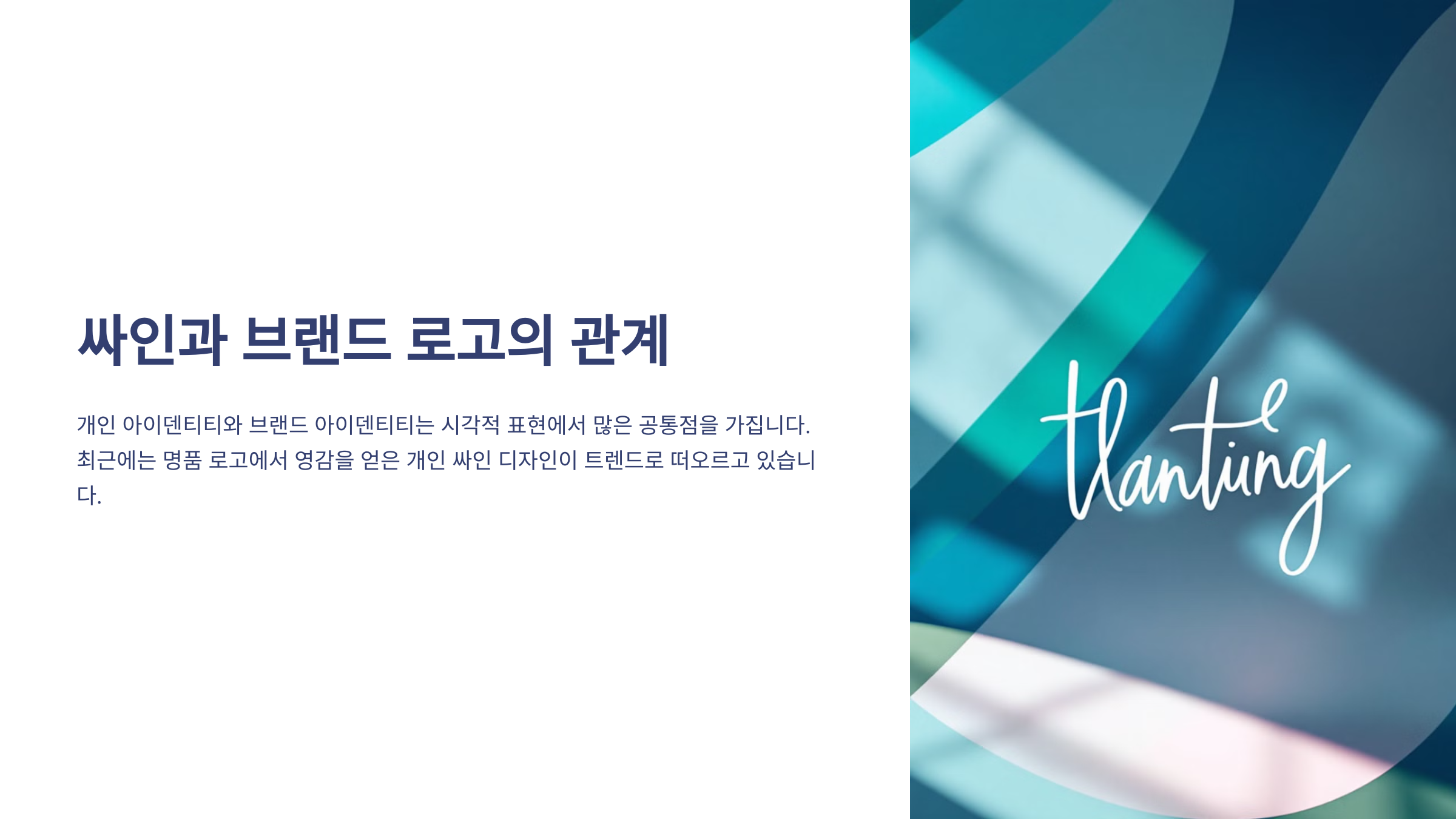
싸인과 브랜드 로고는 단순한 서명이 아니라, 자신의 개성과 가치를 표현하는 중요한 도구예요. 💎
명품 브랜드 로고는 시간이 지나도 변하지 않는 아이덴티티를 가지고 있으며, 싸인도 마찬가지로 한 번 정하면 오랫동안 유지되는 개인의 상징이 될 수 있어요. ✍️
📌 싸인과 명품 브랜드 로고의 공통점 ✅
공통점 설명 예시 고유한 정체성 개인을 상징하는 유니크한 요소 포함 샤넬 "CC" 로고, 나이키 "Swoosh" 간결하면서도 강렬한 디자인 복잡하지 않지만, 강한 인상을 줌 애플 로고, 루이비통 "LV" 시간이 지나도 변하지 않는 가치 한 번 정하면 오래도록 유지 롤렉스 크라운 로고 시그니처 효과 이름 없이도 브랜드나 사람을 인식할 수 있음 펜디 "FF", 마이클 잭슨의 싸인 이처럼 싸인과 브랜드 로고는 비슷한 특징을 공유하고 있어요. 그럼 이제 명품 브랜드 로고의 구체적인 디자인 특징을 살펴볼까요? 👑
명품 브랜드 로고의 특징 👑
명품 브랜드 로고는 단순하지만 강렬한 디자인을 가지고 있어요. 대부분 고유한 아이콘, 이니셜 조합, 세련된 서체를 활용하여 브랜드 가치를 강조하죠. 💎
예를 들어, 샤넬(CHANEL)의 "CC" 로고는 단순하지만 우아한 느낌을 주며, 루이비통(Louis Vuitton)의 "LV" 모노그램은 브랜드의 정체성을 강하게 각인시켜요. ✨
📌 명품 브랜드 로고의 주요 디자인 요소 🎨
디자인 요소 설명 예시 브랜드 이니셜 조합 브랜드의 첫 글자를 활용하여 심볼화 루이비통 "LV", 샤넬 "CC" 대칭적 디자인 균형감 있는 형태로 시각적 안정감 제공 구찌 "GG", 롤렉스 크라운 세련된 필기체 손글씨 스타일의 우아한 서체 활용 조르지오 아르마니, 디올 미니멀한 디자인 불필요한 요소 없이 단순하고 고급스러움 애플, 발렌시아가 명품 브랜드 로고는 고유한 스타일을 유지하면서도 단순하고 세련된 디자인을 갖추고 있어요. 그럼 이제 캘리그래피 스타일 로고를 활용한 싸인 디자인을 살펴볼까요? ✍️
캘리그래피 스타일 로고 ✍️
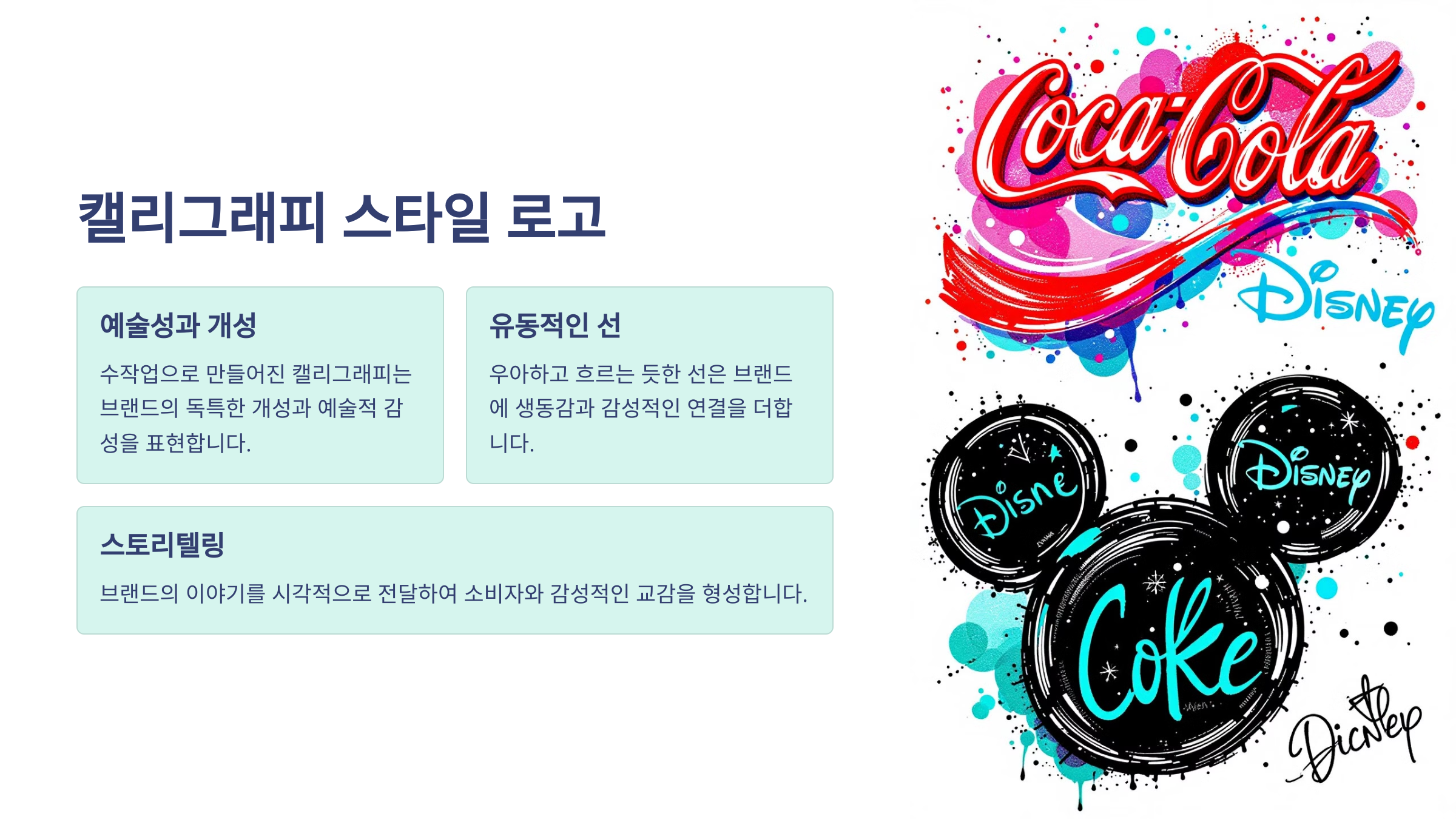
캘리그래피 스타일의 로고는 우아하고 세련된 필체를 활용하여 브랜드의 개성을 강조해요. 특히 패션 브랜드, 뷰티 브랜드, 고급 레스토랑에서 많이 사용되죠. 🎨
예를 들어, 디올(Dior)과 조르지오 아르마니(Giorgio Armani)의 로고는 고급스러운 필기체를 사용하여 브랜드의 품격을 나타내요. 💎
📌 캘리그래피 스타일 로고의 특징 🖋️
특징 설명 예시 브랜드 우아한 필기체 부드럽고 흐르는 듯한 글자 형태 디올(Dior) 곡선과 장식 강조 곡선적인 디자인을 활용하여 개성 표현 조르지오 아르마니(Giorgio Armani) 클래식한 감성 고전적인 아름다움을 강조 까르띠에(Cartier) 고급스러운 브랜드 이미지 브랜드의 가치와 품격을 표현 입생로랑(YSL) 캘리그래피 스타일은 우아한 분위기를 원하는 싸인 디자인에 적합해요! 그럼 이제 모노그램 스타일 로고를 활용한 싸인을 살펴볼까요? 🔤
모노그램 스타일 로고 🔤
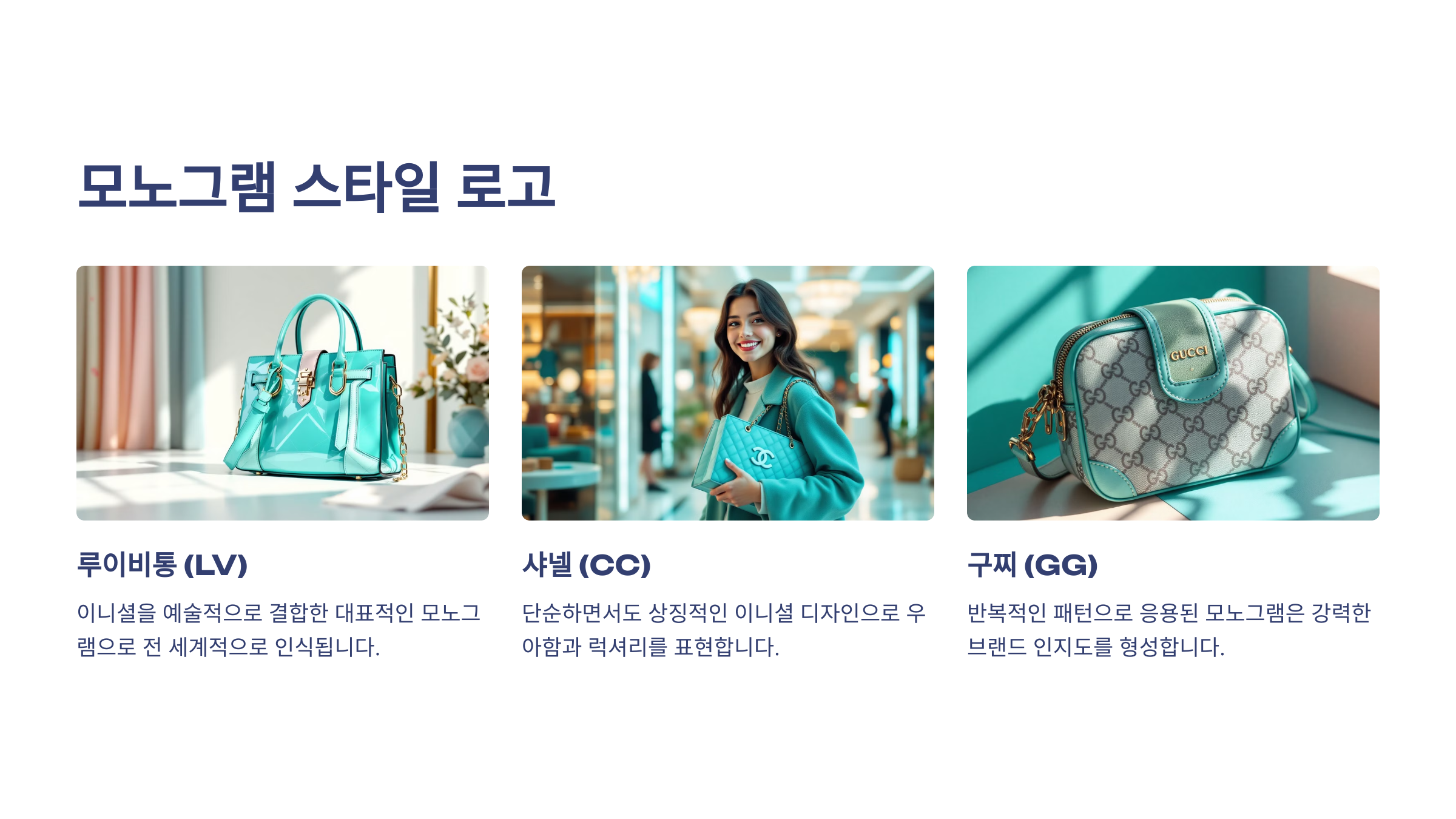
모노그램 스타일 로고는 브랜드의 이니셜을 조합하여 강렬한 아이덴티티를 형성하는 방식이에요. 특히 명품 패션 브랜드에서 많이 활용되며, 싸인 디자인에도 적용할 수 있어요. 💎
예를 들어, 루이비통(Louis Vuitton)의 "LV", 구찌(Gucci)의 "GG", 입생로랑(YSL) 로고는 단순하지만 고급스럽고 강렬한 브랜드 이미지를 전달해요. 🎨
📌 모노그램 스타일 로고의 특징 🏆
특징 설명 예시 브랜드 이니셜 조합 브랜드 이름의 앞글자를 디자인적으로 배치 루이비통 "LV" 대칭적이고 균형 잡힌 형태 글자 간격과 배치를 정교하게 맞춤 구찌 "GG" 타이포그래피 강조 독특한 글씨체를 활용하여 브랜드 개성 표현 입생로랑 "YSL" 시각적 인지도가 높음 한 번 보면 쉽게 기억할 수 있는 디자인 펜디 "FF" 모노그램 스타일은 단순하면서도 고급스러운 싸인을 만들고 싶을 때 참고하면 좋아요! 그럼 이제, 미니멀하고 세련된 스타일의 브랜드 로고를 활용하는 방법도 살펴볼까요? ✨
미니멀하고 세련된 로고 ✨
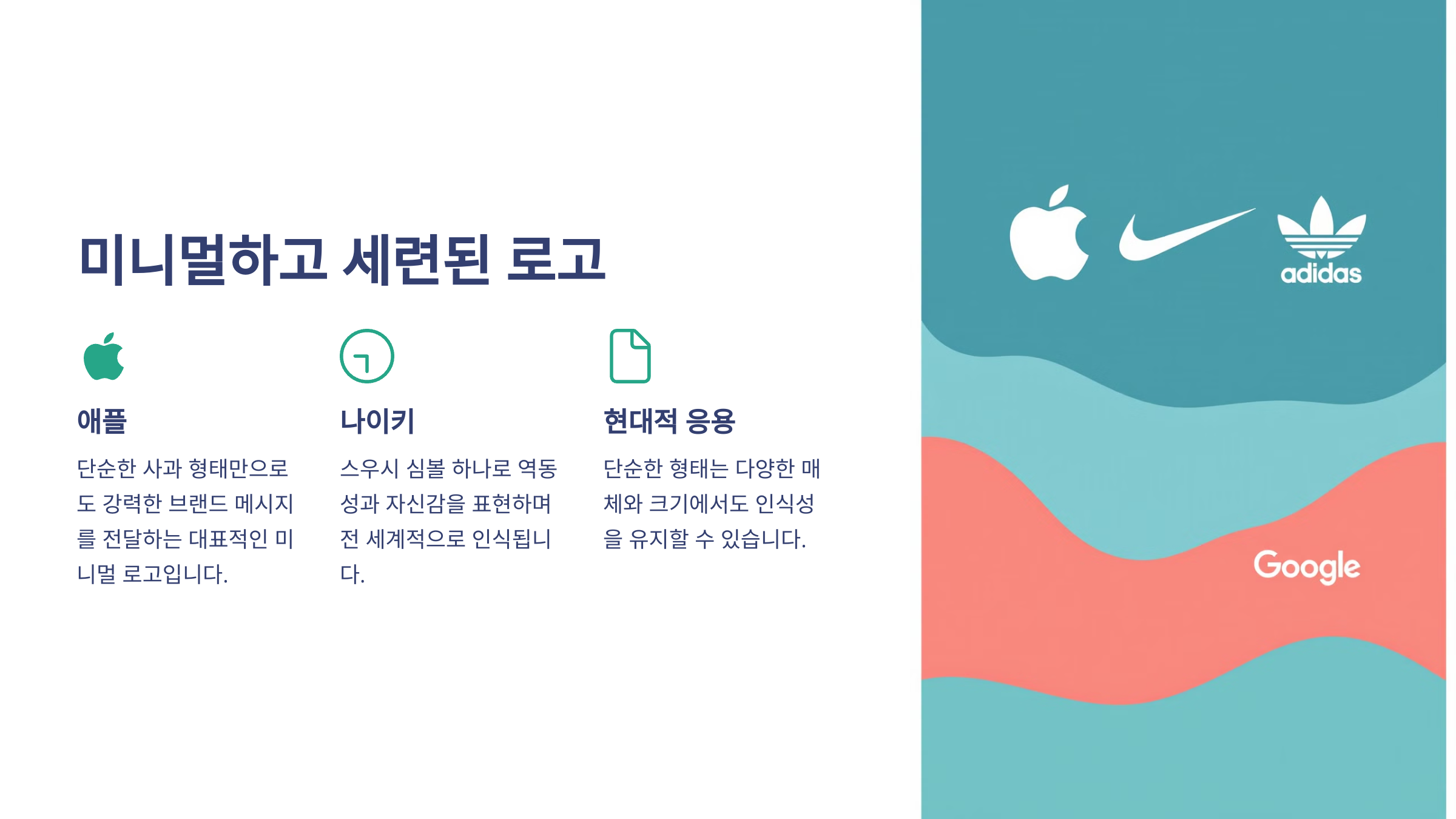
미니멀한 디자인은 불필요한 요소를 제거하고, 본질적인 아름다움을 강조하는 스타일이에요. 이는 싸인 디자인에서도 적용할 수 있으며, 깔끔하면서도 세련된 느낌을 줄 수 있어요. 💎
예를 들어, 애플(Apple), 발렌시아가(Balenciaga) 같은 브랜드는 최소한의 요소만 사용하여 강렬한 브랜드 이미지를 구축했어요. 🔥
📌 미니멀한 스타일 로고의 특징 🎨
특징 설명 예시 브랜드 단순한 타이포그래피 깔끔한 글씨체만 사용하여 브랜드 이미지 전달 발렌시아가(Balenciaga) 불필요한 요소 제거 장식 없이 직관적인 디자인 애플(Apple) 균형과 정렬 글자 간격과 형태의 정교한 조화 마르니(Marni) 색상 최소화 단색 또는 블랙&화이트 활용 셀린(Celine) 미니멀한 스타일은 심플하면서도 강렬한 인상을 남길 수 있어요. 이제 명품 로고의 특징을 활용해 나만의 싸인을 디자인하는 방법을 알아볼까요? ✍️
명품 로고를 참고해 싸인 디자인하는 법 ✍️
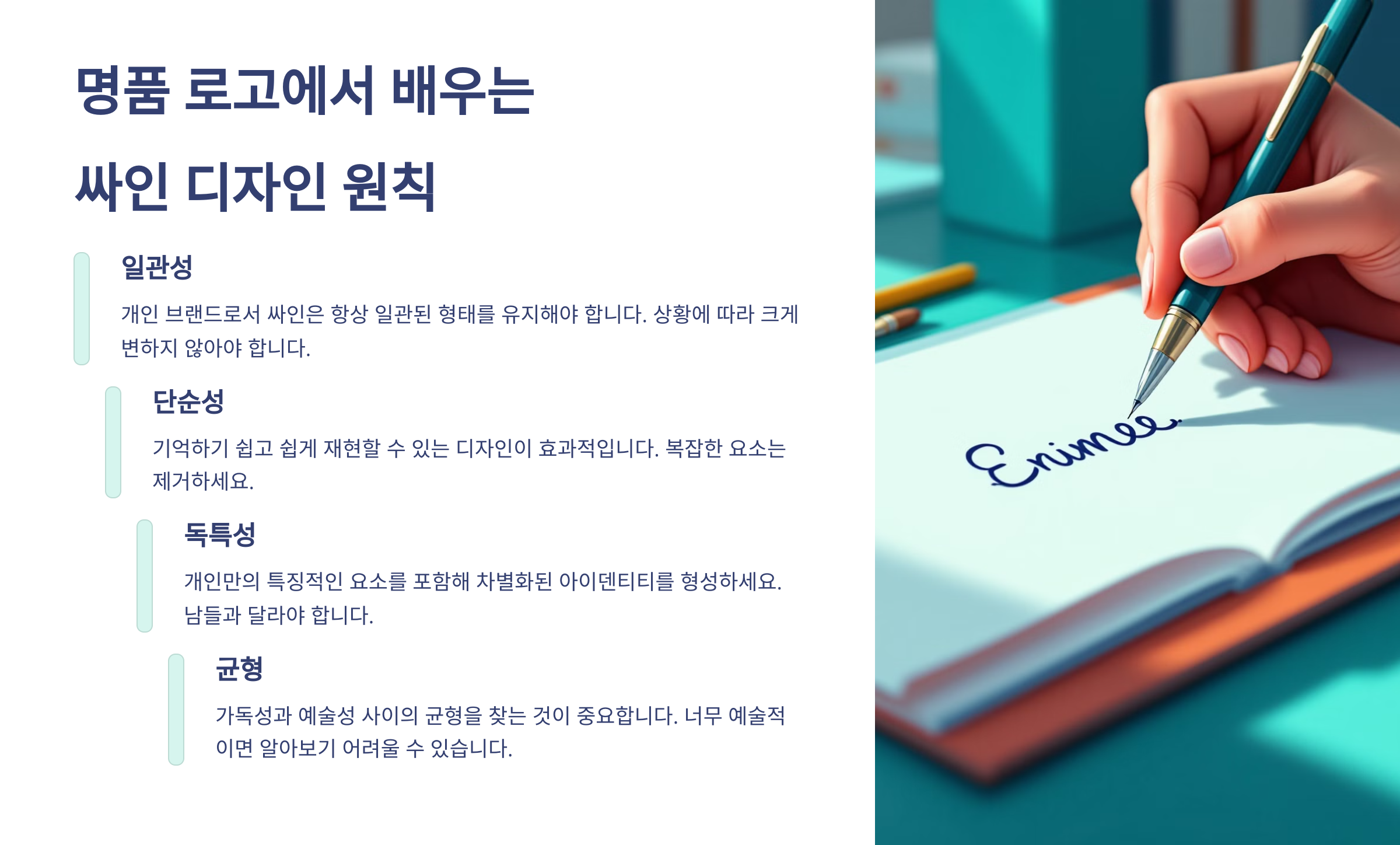
명품 브랜드 로고의 디자인 원칙을 활용하면, 단순하면서도 고급스럽고 개성 있는 싸인을 만들 수 있어요. 💎
지금부터 명품 브랜드 로고에서 배울 수 있는 싸인 디자인 원칙을 알려드릴게요. 🚀
📌 명품 로고를 활용한 싸인 디자인 5단계 ✅
단계 설명 참고 브랜드 1. 간결한 형태 유지 복잡한 장식을 피하고 핵심 요소만 남기기 샤넬(CHANEL), 애플(Apple) 2. 이니셜 활용 이름의 첫 글자를 활용해 스타일링 루이비통(LV), 구찌(GG) 3. 필기체 또는 정형화된 서체 선택 우아한 필기체 또는 세련된 타이포그래피 활용 디올(Dior), 입생로랑(YSL) 4. 균형과 대칭 유지 글자 간격과 정렬을 맞춰 안정적인 디자인 롤렉스(Rolex), 마르니(Marni) 5. 자신만의 포인트 추가 별(★), 밑줄, 곡선 등 개성을 살리는 요소 추가 마이클 잭슨의 싸인, 펜디(FF) 이제 명품 브랜드 로고의 특징을 반영한 나만의 싸인을 만들 준비가 되었어요! 마지막으로, 싸인과 브랜드 로고에 대한 자주 묻는 질문(FAQ)을 정리해 볼게요. 📢
FAQ
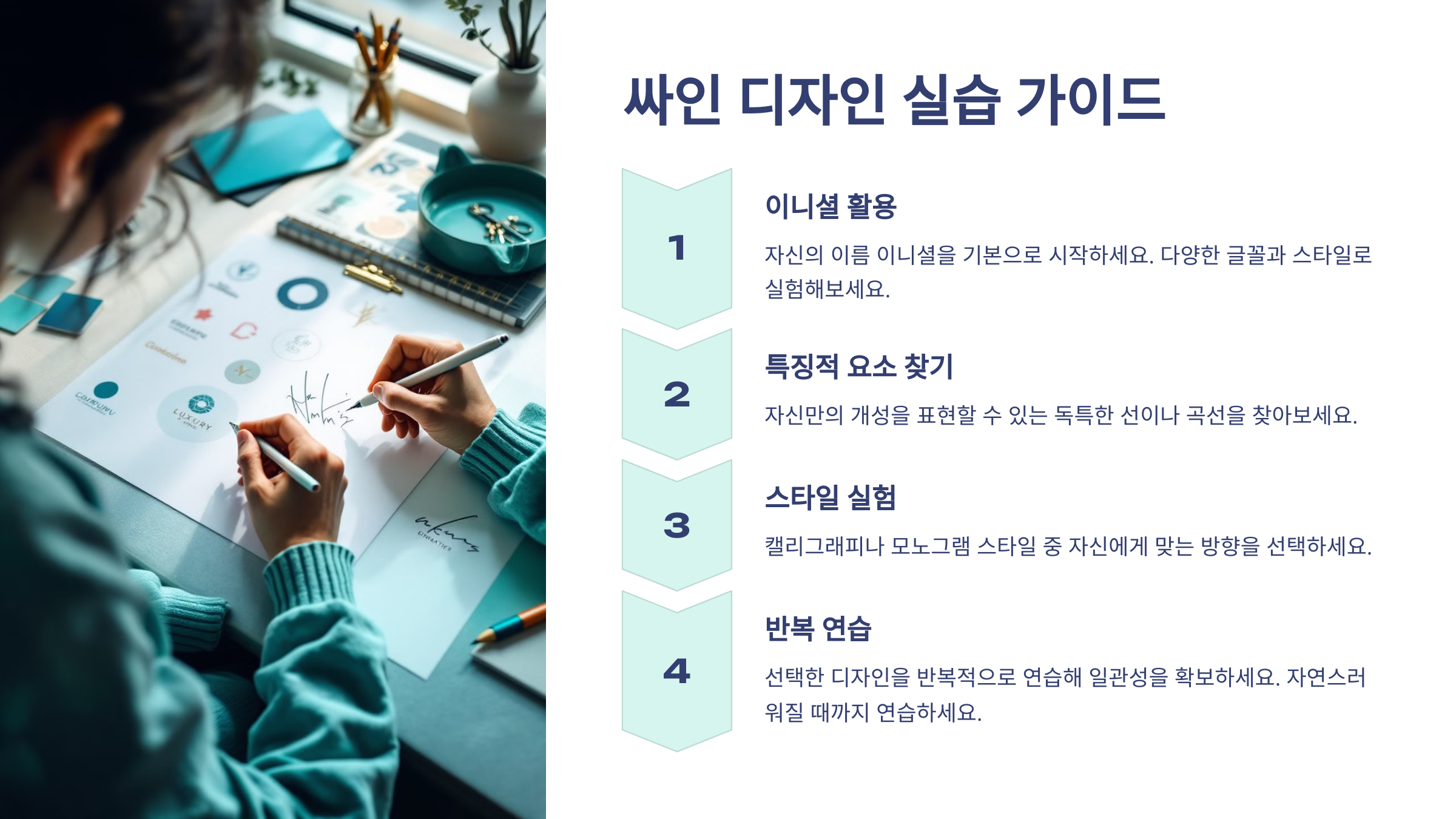
Q1. 싸인과 브랜드 로고는 어떤 점이 비슷한가요?
A1. 둘 다 단순하지만 강렬한 인상을 남기며, 아이덴티티를 강조하는 역할을 해요. ✍️
Q2. 싸인을 만들 때 이니셜을 활용하면 어떤 장점이 있나요?
A2. 이니셜을 활용하면 짧고 강렬한 싸인을 만들 수 있으며, 기억하기 쉬워요. 🔤
Q3. 명품 브랜드처럼 세련된 싸인을 만들려면 어떻게 해야 하나요?
A3. 간결한 디자인, 대칭적인 형태, 필기체 또는 정형화된 서체를 활용하면 더욱 세련된 싸인을 만들 수 있어요. 💎
Q4. 싸인에 밑줄이나 심볼을 추가해도 괜찮을까요?
A4. 네! 하지만 너무 과하면 가독성이 떨어질 수 있으니 적절한 크기로 활용하는 것이 중요해요. ⭐
Q5. 싸인을 정할 때 컬러를 신경 써야 하나요?
A5. 공식 문서에서는 검정 또는 파란색이 일반적이지만, 개인 브랜딩용 싸인은 자유롭게 컬러를 활용할 수 있어요. 🎨
Q6. 싸인을 너무 단순하게 하면 안 좋은 점이 있나요?
A6. 너무 단순하면 위조가 쉬울 수 있어요. 개성을 살리면서도 고유한 특징을 넣는 것이 중요해요. 🔍
Q7. 명품 브랜드 로고처럼 싸인을 만들려면 가장 중요한 요소는?
A7. 균형, 간결함, 개성이 가장 중요해요. 싸인이 너무 복잡하면 인상적이지 않을 수 있어요. ⚖️
Q8. 싸인을 연습할 때 어떤 점을 가장 신경 써야 하나요?
A8. 일관성 있게 반복해서 연습하는 것이 중요해요. 한 번 정한 스타일을 계속 유지하면 자연스럽게 손에 익어요! 🖋️